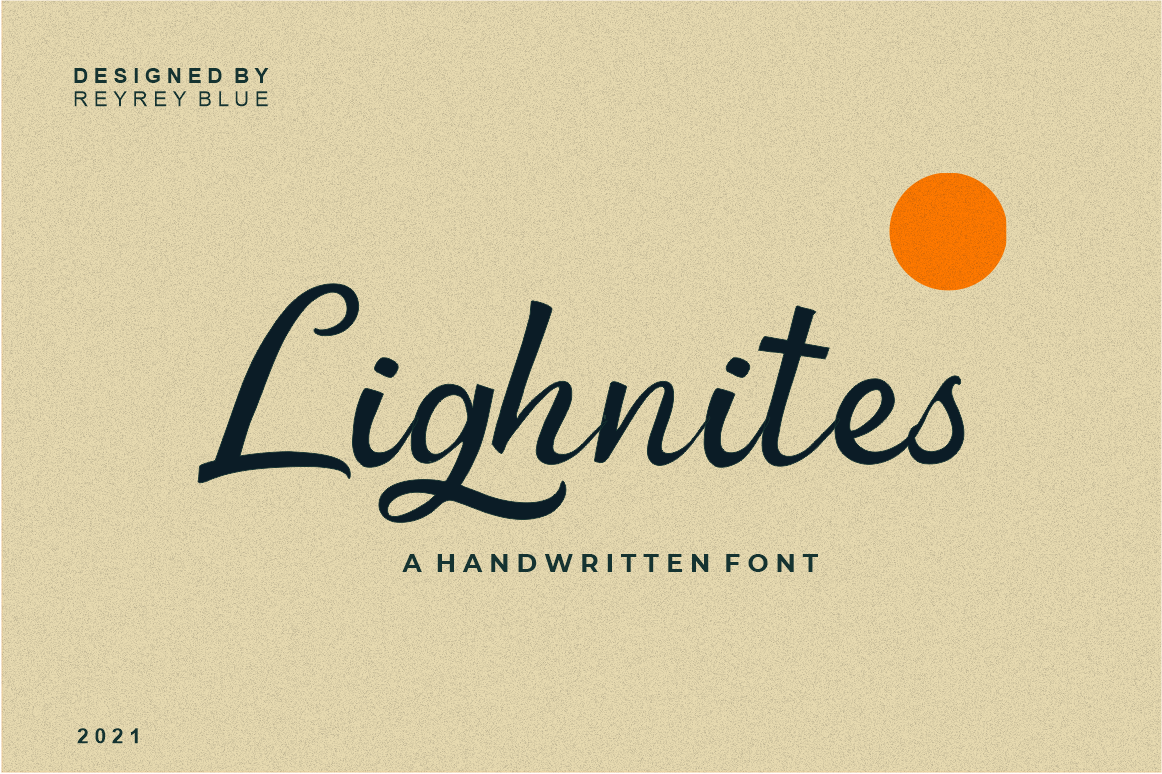
Lighnites Font – Download Grátis
A ‘Lighnites Font’ é uma elegante tipografia feita a mão, com traços delicados que lembram as escritas de alguém que tem a habilidade única de criar um texto à mão. Suave e fino, essa fonte original será adorada por criadores talentosos em diversas áreas, desde design de assinaturas e títulos até papelaria. Se você busca uma maneira sofisticada e suavemente delicada para personalizar seu trabalho gráfico ou projeto, ‘Lighnites Font’ é sua escolha perfeita. Suas curvas delicadas se destacam, criando um ar delicado e acolhedor que é capaz de se adaptar a um amplo espectro de usos. Seja para decorar cartões personalizados ou até mesmo criar identidades visuais únicas, essa fonte será uma excelente escolha. Sem dúvida, o seu projeto ganhará profundidade com a ‘Lighnites Font’.